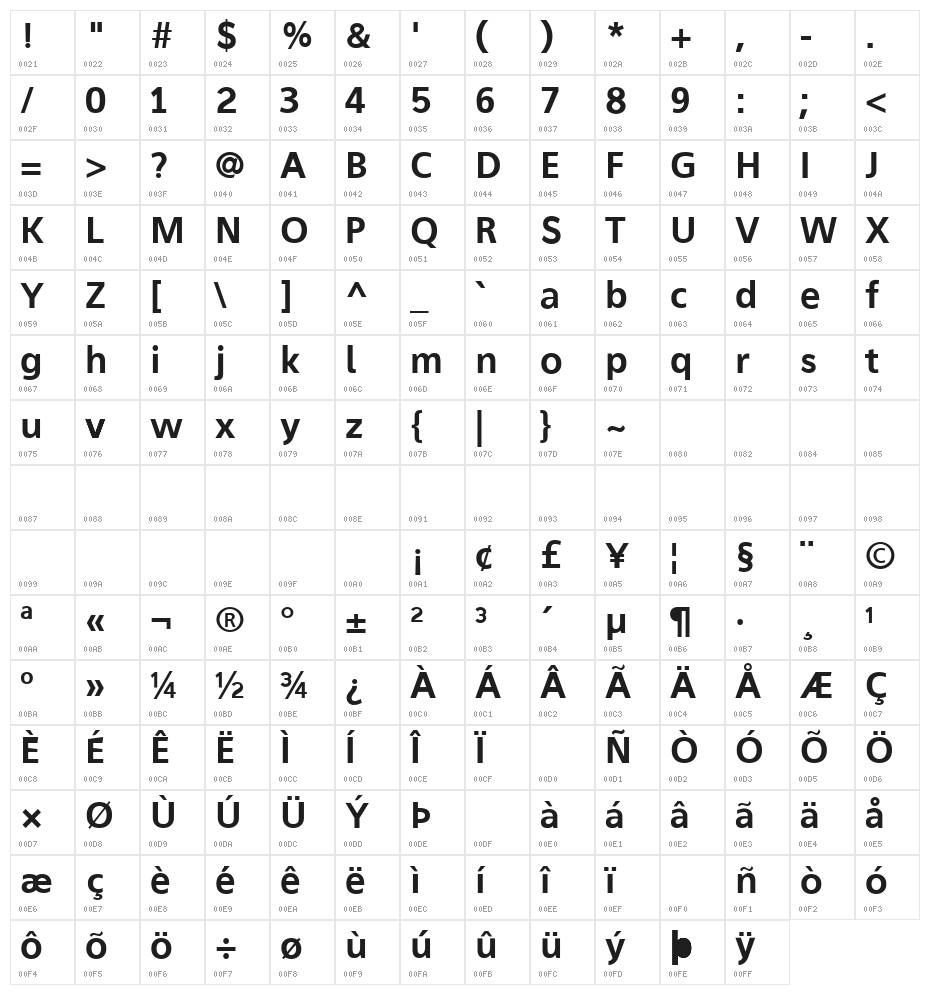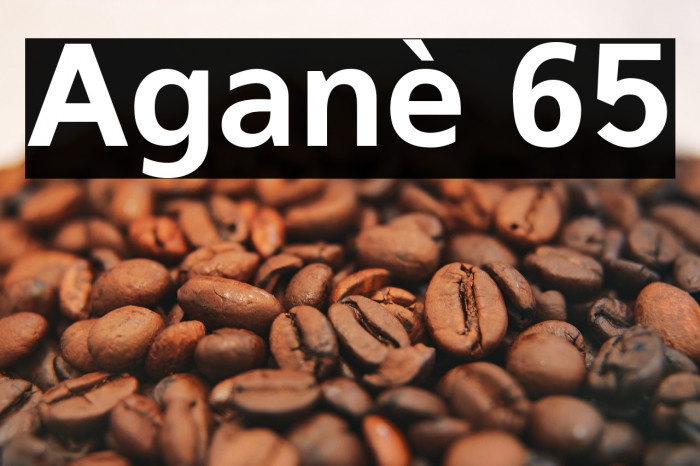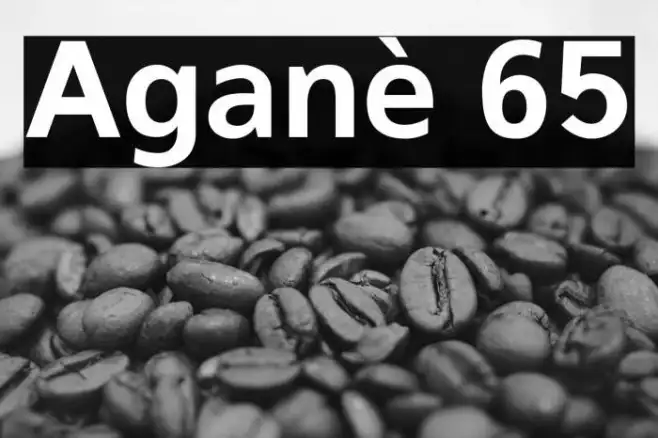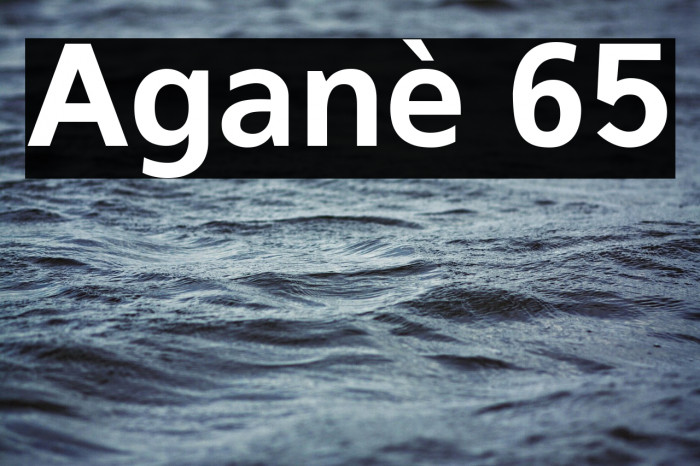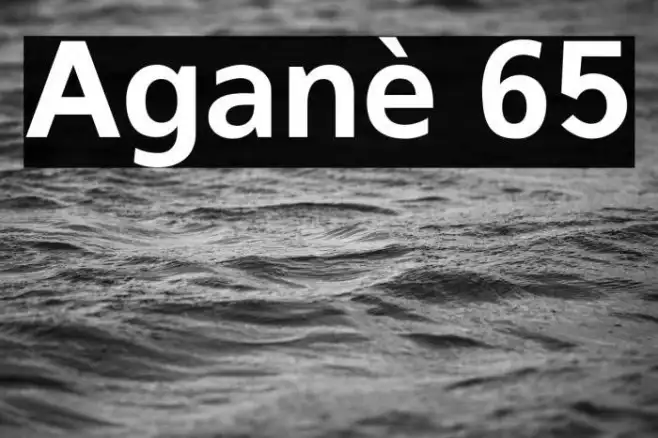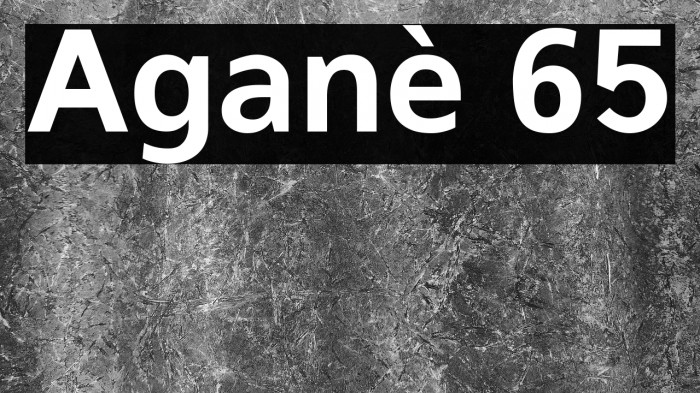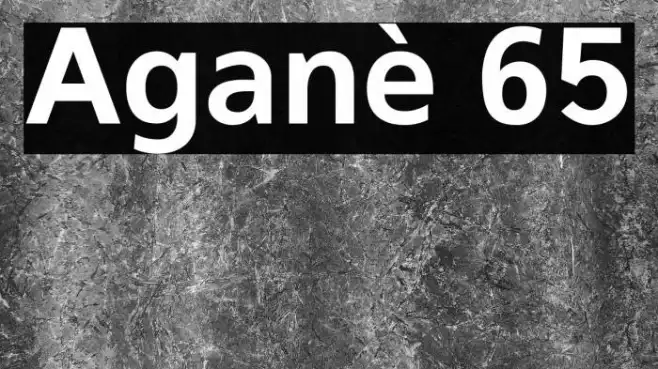
Aganè 65 Font
| Cas d'utilisation | Headlines, Logos, Body text |
| Projets proposés | Ideal for branding, advertising, web design, and editorial projects where clarity and modernity are key. |